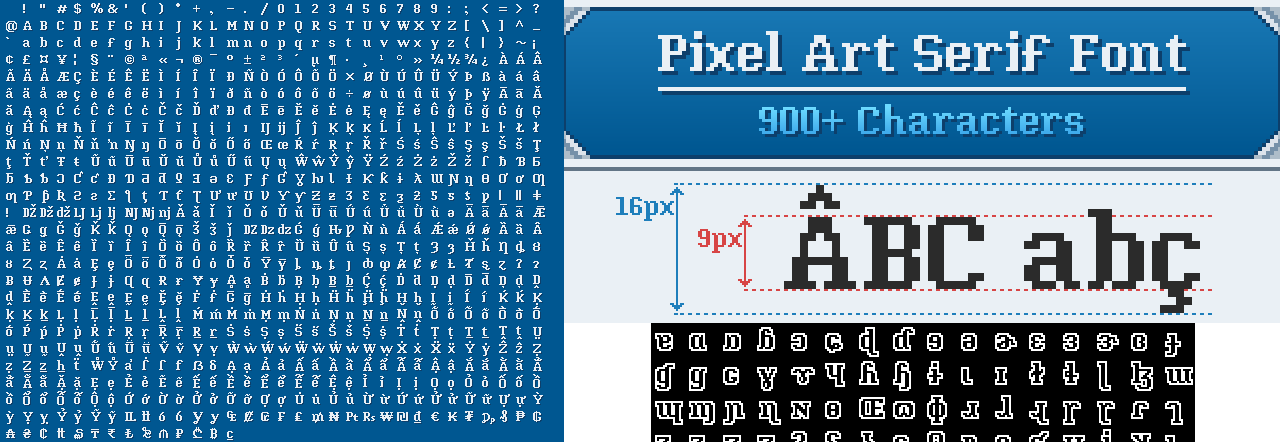
Шрифт «Pixelart Serif Font» v0.2
Reff Pixels по лицензии Creative Commons Attribution NoDerivatives v4.0 International выложил шрифт «Pixelart Serif Font» в стиле Pixel Art, содержащий более 900 символов 16x16. Он может использоваться при разработке игр для хорошо читаемого текста в диалогах и пользовательском интерфейсе.